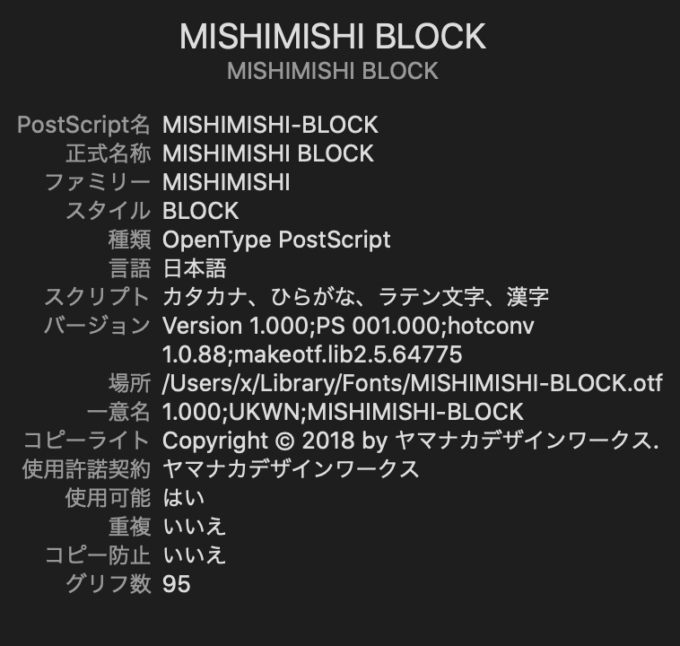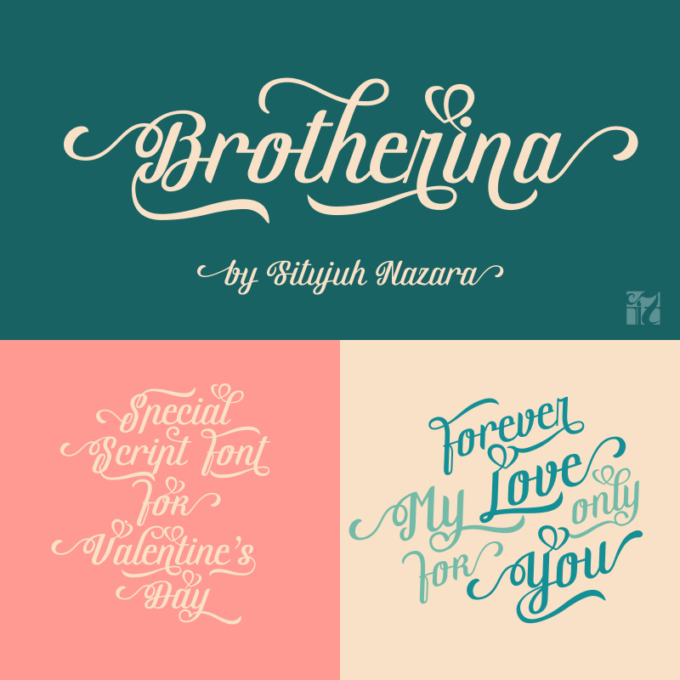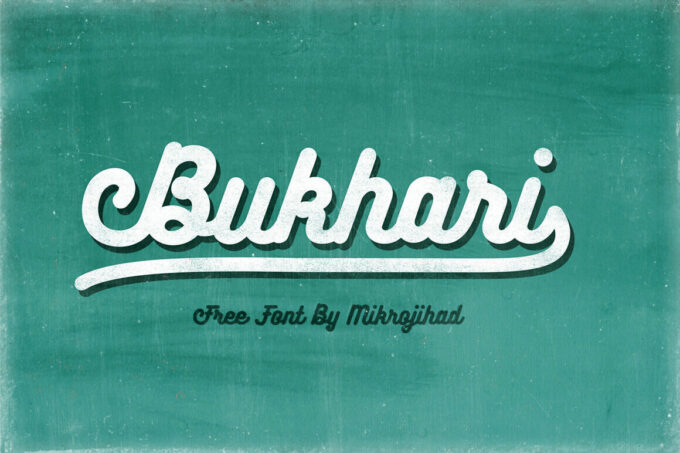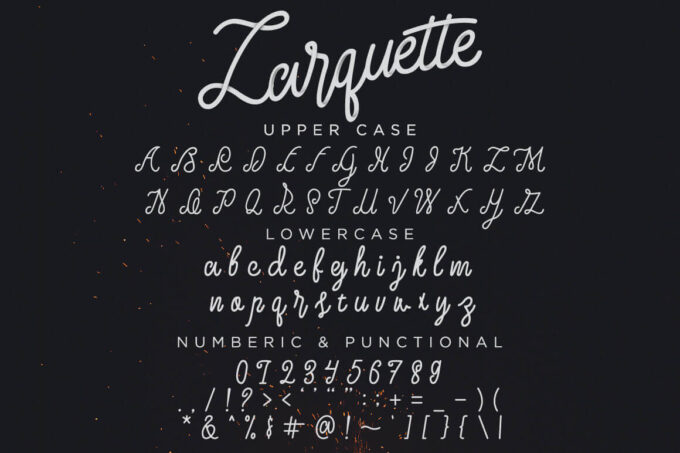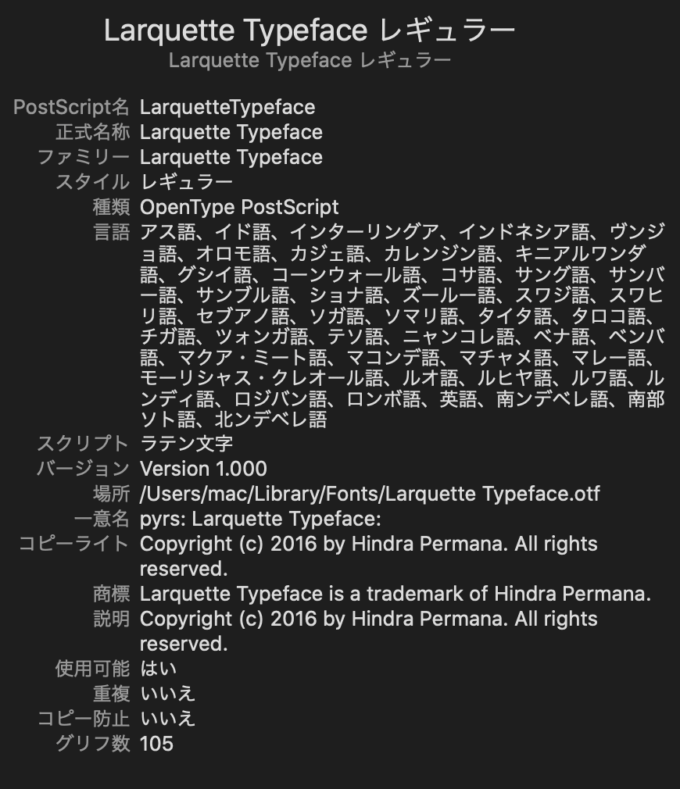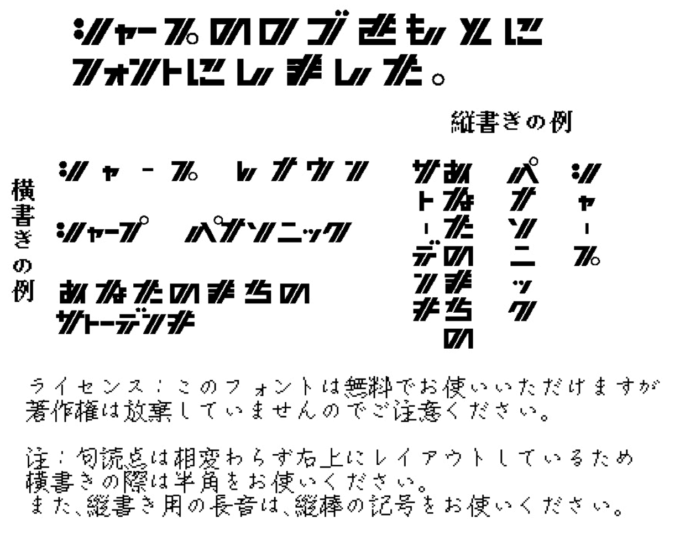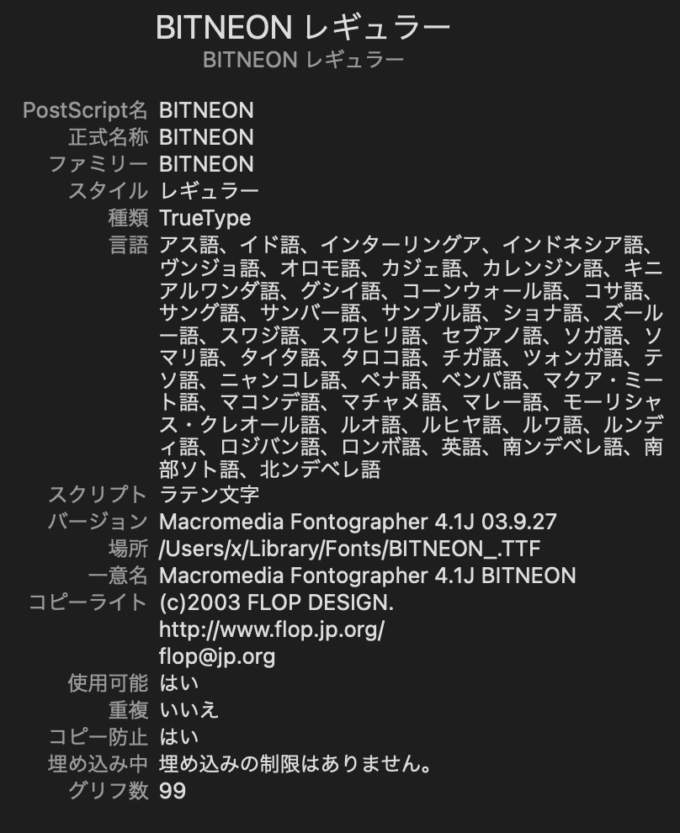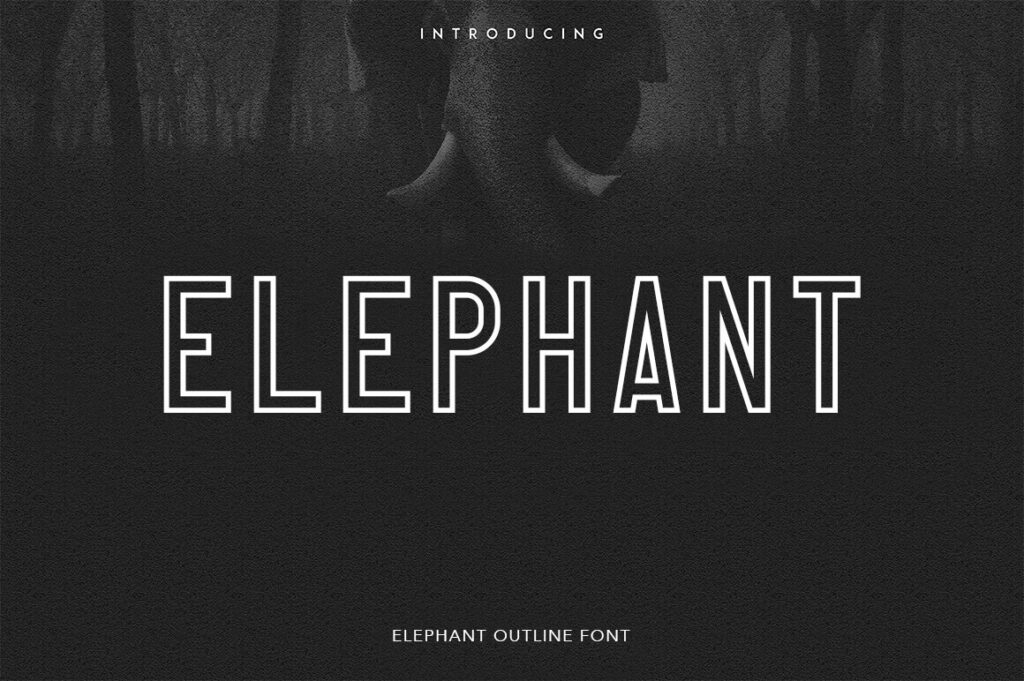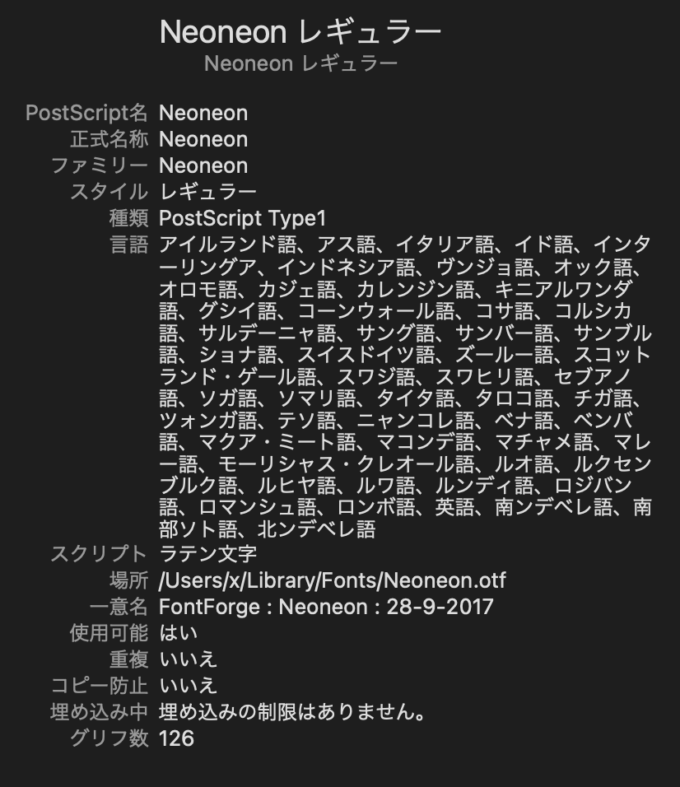
ネオンサインはかっこいいんだけど表現の仕方を間違うと逆にダサくなっちゃうから注意が必要だよd( ̄  ̄;)
それなら…ただ光らせるだけで簡単にネオンサインがかっこよく見える
無料フォントがあるから、ちょっと紹介してみるね d(^^)
今回はネオンサインのデザインに使える『無料フォント素材』を紹介していきますd( ̄  ̄)
「テキストにグローをかけてもイマイチカッコよく決まらない…」という悩みをお持ちの方に
とりあえず『光らせればカッコよく見える』というコンセプトで素材をチョイスしているので、グローをかけるだけでそれなりにカッコよく見えるかと思います\( ̄∀ ̄)/
Neoneon
Trias
ビットネオンフォント
Elephant Font
HALFOMANIA
まるこいあす
Potra Free Font Typeface
TRON
JURASSIC PARK
Cars
Bukhari
Brotherina Script Font
Larquette Typeface
Santana
Delight Lettering
STAR WARS
Walt Disney
チェリーチェリー
フルーツパーラーmini
70:TIROLING
70:DOUToR
コトダマ
EXPOSITION
魔法陣文様フォント『Magic Ring』
魔法陣文様フォント『猫の目覚め』
x12y16pxLineLinker
Electronic Highway Sign
1010
Clubland
Gas
Neon Tube